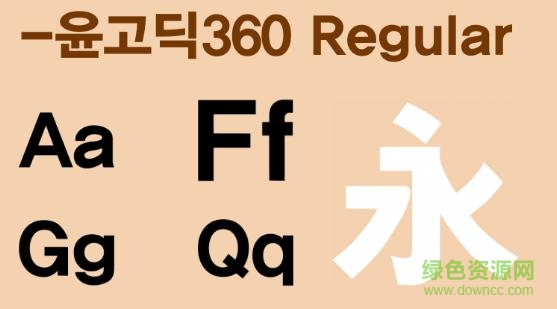
ydiygo360 字體是一款硬朗有力的韓文字體,字面版面通透,結(jié)構(gòu)協(xié)調(diào)一致,整體字形大方豪邁,適合屏幕的用字需求以及平面設(shè)計(jì)的需求,歡迎大家免費(fèi)下載!
力道、堅(jiān)實(shí)、沖擊、厚重、硬朗、猛烈 …… 這類(lèi)字體氣勢(shì)突出,視覺(jué)沖擊力明顯,個(gè)性張揚(yáng)有力,節(jié)奏分明,可以用于變現(xiàn)強(qiáng)烈的信心和勇氣,表現(xiàn)凝聚力和號(hào)召力,給人視覺(jué)上的震撼。 這類(lèi)字形因其字形富有張力,所以在表現(xiàn)刺激,冒險(xiǎn)的情景時(shí)比較常用,如體育活動(dòng)、極限運(yùn)動(dòng)的主題同時(shí)戰(zhàn)爭(zhēng)類(lèi)、災(zāi)難類(lèi)電影海報(bào)中,這類(lèi)字形也比較常見(jiàn)。